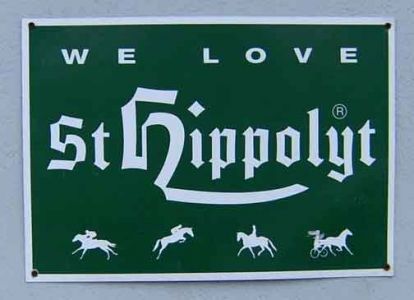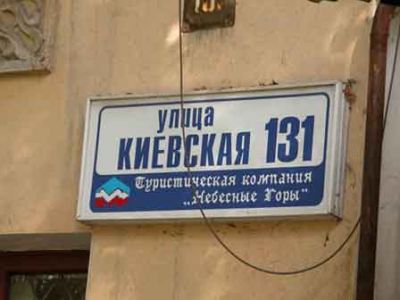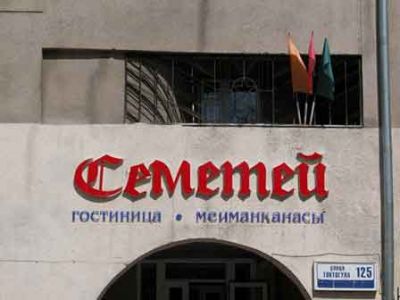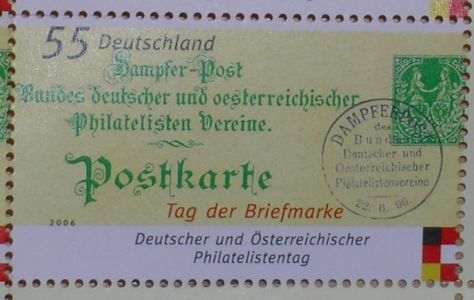
Gebrochene Schriften, noch aktuell?
Ich wollte dem von Georg, dem Bleisetzer, ergangenen Spendenaufruf Folge leisten und meinen Obolus in Form von Briefmarken einsenden. Doch dann sah ich, dass auch die Briefmarke der Deutschen Post AG kein langes s nutzt:
Schade eigentlich; ich hatte die Briefmarke gerade wegen der gebrochenen Schrift gekauft. Ich hätte halt genauer hinsehen sollen.
Wer kennt es nicht: Der Klassiker des falschen "s" in Gebrochenen Schriften ist doch stets das "Gasthaus zur Post". Wahrscheinlich haben da Kölner Philatelisten ihren Stammtisch.
Ich erwähne das, weil ich mal für ein Gasthaus zur Post aus Gefälligkeit einen "Flyer" gemacht habe. Und als ich das Wirtshausschild korrekt gesetzt hatte, lasen die Wirtsleute immer "Poft" ... Man kann sich denken, wie das ausging.
das ö gab es in der schrift anscheind auch nicht - amerikanischer font?
Aber müßte man diese Herausgeber denn dann nicht anschreiben und protestieren? Ich meine: Niemand zwingt sie, Gebrochene Schriften zu verwenden. Man freut sich halt, wenn.. Aber dann doch bitte auch korrekt - oder überhaupt nicht. Beim Kölsch kann ich das ja noch irgendwo verstehen. Marketing-Fuzzis halt. Aber bei der Deutschen Post?
ich bin übrigens auch für den wegfall des langen s, sofern es um die 'neuen gebrochenen' schriften geht, dadurch hätten es diese schriften einfacher sich international durchzusetzten. die fakir von underware macht das ja gut vor. mit langem s gern als alternative variante für den deutschen sprachraum (ähnlich ß).
neue gebrochene schriften:
http://www.fugit-tempus.de/progothics/pg_modern.htm
Ich sehe zwei Sichtweisen:
1. Bewahren der Tradition, also korrekter Fraktursatz.
2. Anwendung der Fraktur als ›gewöhnliche‹ Schrift, wie also auch Antiqua, Grotesk, handschriftliche Antiqua etc. — also nach den derzeit üblichen Satzregeln — was wohl eine breitere ›Verständlichkeit‹ fördern würde.
Ob jemand Fraktursatz flüssig lesen kann, hängt wohl weniger mit Hauptschulabschluss zusammen als viel mehr mit dem Alter — es sei denn eure Schüler in Düsseldorf lernen in der Hauptschule die gebrochenen Schriften noch lesen.
Ich stehe diesen beiden Sichtweisen (derzeit) wertungsfrei gegenüber.
Es geht mir nicht darum, vom hohen Roß (Welchem? Ich habe nicht einmal Abitur) mangelndes Bildungsniveau zu beklagen.
Es ging mir darum, der Werbung zu unterstellen, ein immer niedrigeres GGV finden zu müssen, um eine größere Zielgruppe anzusprechen.
GGV? Größtes Gemeinsames Vielfache.
Konkret:
"Laßt uns auf das Lang-s bei diesem 'Fraktur'-Schriftzug verzichten. Das versteht heutzutage eh niemand mehr und dann können wir dennoch diesen tollen 'antiken' Charakter dieser 'Fraktur' nutzen."
Ich finde nun leider kein Bild mehr davon, aber hat jemand diesen September die Inhouse-Plakate im zur Herbstkollektion von C&A gesehen? Da stand in gebrochener Schrift "Herbstkollektion", und ich erinnere mich an das fraktur-k, und dass Jungendliche verwirrt davorstanden, sich aber freuten zu entdecken, dass das ein k sein muss. Leider weiß ich nicht wie es da mit dem s aussah... Meinen spärlichen Kenntnissen zufolge müsste in "Herbst" ja auch ein langes s stehen, richtig?
Ja, genauer: eine "Lang-s t-Ligatur".
Ich find's prima. Wann bleiben schon Jugendliche mal vor einem Plakat stehen und rätseln über Schrift? Ist doch toll.
viele amerikanische und
englische frakturen haben kein langes-s.
Ja, das stimmt. Aber die haben auch keine Umlaute "ä, ö und ü".
So what?
Was sagt es aus, wenn Du schreibst "viele amerikanische und
englische frakturen haben kein langes-s." ? Besser: Was willst Du damit aussagen?